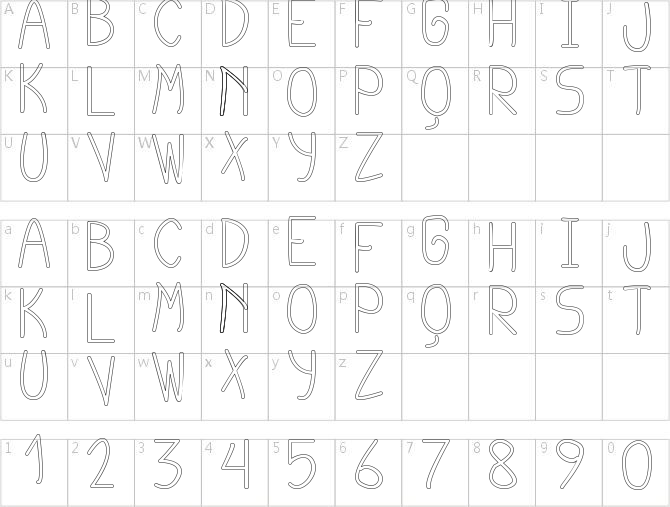
cursi-extra-tfb-hollow
cursi-extra-tfb-hollow字體字庫(kù)是一款讓人賞心悅目、百看不厭的英文字體,適合各類廣告和產(chǎn)品包裝設(shè)計(jì)應(yīng)用,字體大小0.02MB,格式為ttf字體,上傳用戶是伍佰,作者/版權(quán)方為未知